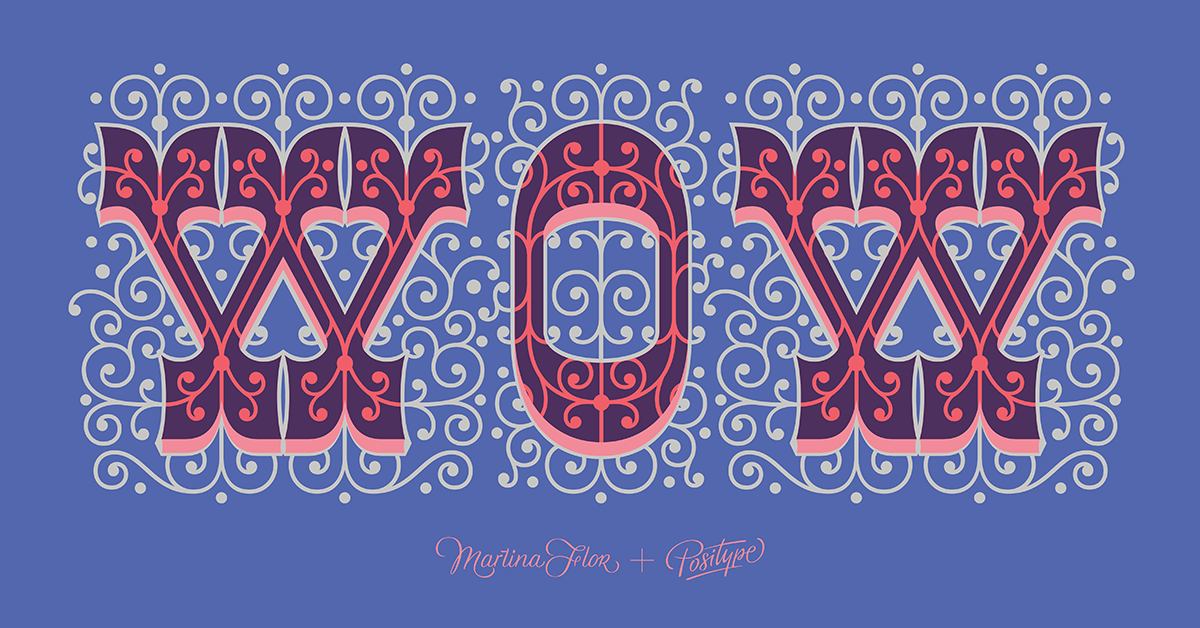
Martina Flor estrena 'Decorata', la tipografía basada en su lettering
Martina Flor acaba de lanzar Decorata, su primera tipografía inspirada en sus letterings con Positype
Con todos los proyectos de lettering que ha desarrollado Martina Flor (@martinaflor) hasta ahora, ¿cómo es posible que no tuviese todavía una tipografía? Esa es la pregunta que le realizaron a Martina durante una conferencia y que sirvió como detonante para crear, por fin, Decorata, una tipografía basada en su estilo, con los ornamentos y filigranas característicos de sus trabajos de lettering, pero accesible a todo el mundo en forma de tipografía.
De la mano del tipógrafo Neil Summerour, de Positype, Martina diseñó Decorata partiendo de uno de sus letterings dibujando a mano cada letra. Así, juntos, crearon un sistema tipográfico consistente: una familia con ocho estilos diferentes que respeta la necesidad del diseño de controlar todos los aspecto del diseño y la expresividad de la letra.
Decorata - Martina Flor
Cada estilo de Decorata funciona por separado, pero esta tipografía ha sido diseñada de tal manera que unas capas puedan superponerse sobre las otras aumentando la capacidad expresiva de la tipografía. El estilo Regular de Decorata define las formas de las letras, Shadow aporta profundidad y Outline sirve para delimitar el alcance de los ornamentos; por su parte, los estilos Intricate y Filigree varían el grosor de los glifos; Lace elimina los tirabuzones externos de las letras, conservando el espacio negativo de las líneas decorativas; Fancy muestra un glifo con peso y decorado y Dingbats es una colección de complementos para terminar de redonderar una tipografía inspirada en un lettering excepcional.
Decorata - SorayaCremalle
En este sentido Decorata es diferente a otras tipografías; mientras otras persiguen, generalmente, una finalidad comunicativa precisa, Decorata se entrega al ornamento, convirtiéndose en una opción idónea para cubiertas de libros, pósteres, tarjetas... en definitiva, todos esos soportes en los que usaríamos el lettering.
Martina Flor - SorayaCremalle
Decorata - Martina Flor